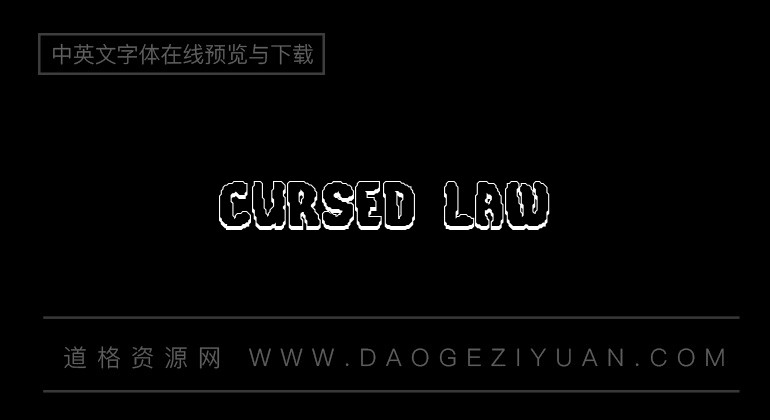
Cursed Law 字体是一种装饰性的字体,其设计灵感来自于黑魔法和强大的魔法力量的概念。它的字母和符号都具有浓厚的魔法气息,使其在设计魔法主题的项目中非常受欢迎。 Cursed Law 字体的字形特征包括粗犷、扭曲和锐利的线条,以及一些独特的装饰元素,如骷髅头、火焰和血滴。它的字母和符号都呈现出一种浓重的黑色色调,与其他颜色的组合可以产生非常引人注目的效果。 Cursed Law 字体可以用于各种场合,如海报、书籍封面、游戏界面和标志设计等。如果您需要一个具有魔法主题的字体来增强您的设计效果,那么 Cursed Law 字体是一个不错的选择。内容介绍
Cursed Law是一款非常不错的手写艺术字体,具有很好的视觉感,适合于文化类的宣传设计、商业类品牌的广告和产品包装设计以及个性化文字排版等较多场景。